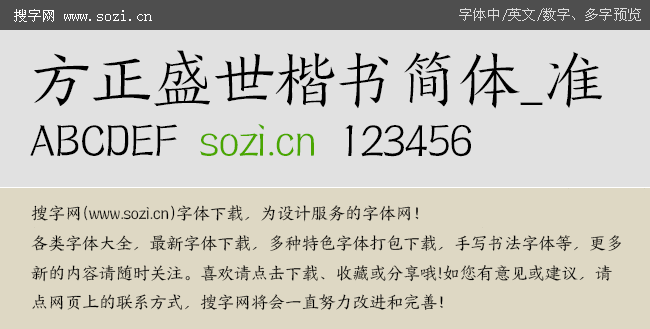
方正盛世楷書簡(jiǎn)體_準(zhǔn)
搜字網(wǎng)提供一款方正盛世楷書簡(jiǎn)體_準(zhǔn)中文字體下載,方正盛世楷書是一款端正的楷體字體,字體大方得體,效果非常漂亮,可以應(yīng)用于美術(shù)設(shè)計(jì)、宣傳海報(bào)、書籍設(shè)計(jì)等領(lǐng)域。